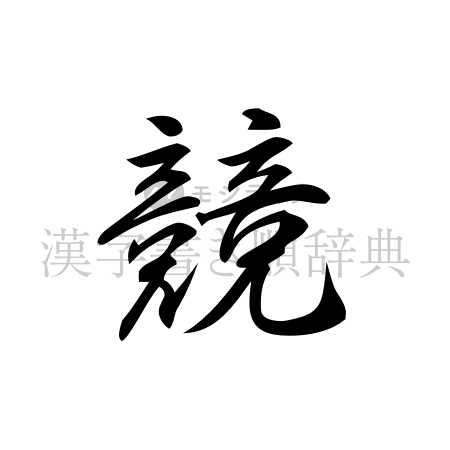
漢字「競」(キョウ)の書き順・読み方・意味・部首・画数
「競」の書き順動画アニメーション(20画)
「競」の読み・画数の基本情報
とある読みは、高等学校で習う漢字の読み方です。
「競」の書体
• 競の書体「ゴシック体」のイメージ
• 競の書体「明朝体」のイメージ
• 競の書体「教科書体」のイメージ
• 競の書体「楷書体」のイメージ
• 競の書体「行書体」のイメージ
• 競の書体「草書体」のイメージ
• 競の書体「隷書体」のイメージ
• 競の書体「篆書体」のイメージ
「競」に形の似た漢字
「競」の意味
• 競うこと。争うこと。
• 競争すること。
• 競り合うこと。
• 競技や試合。
• 競馬や競輪などのギャンブル。
「競」の意味の英訳
漢字は1文字で多様な意味を持ちますが、「競」を英語で表す場合、一般的には emulate, compete with, bid, sell at auction, bout, contest, race などがあります。
「競」の成り立ち・由来
六書分類 会意文字
構造 二人の人+言(誩)を並べた会意
「競」は会意文字です。古い字形は、二人の人が並び立つ姿の上に「言」を重ねた形で成り立っています。二人が言い争い、力や速さをきそい合うようすを、人と言葉を二つずつ並べることで表しました。ここから「きそう」「せる」「あらそう」といった意味が生まれ、競争・競技・競売などに用いられます。現在の字形は、上部が「立」を並べた形、下部が「兄」を並べた形へと整えられ、二つのものが対になって張り合う構造をよく残しています。
※ 細部の字形解釈には諸説あります。
「競」を含む熟語・単語とその意味
競技 - きょうぎ
わざをきそうこと。
競馬 - けいば
競走馬に一定の距離を走らせ順位を競う競技。
競売 - きょうばい
多くの買い手に値段をつけさせ、最も高い値段をつけた人に売る方法。せりうり。けいばい。
「競」の筆画・ストローク構成
「競」の国語施策
「競」は名前に使える漢字です。